MdN(エムディエヌ)2019年4月号
インプレスグループでデザイン分野のメディア事業を手がけるエムディエヌコーポレーションは、デザインとグラフィックの総合情報誌「MdN(エムディエヌ)」2019年4月号を発行した。特集は「平成のグラフィックデザイン史」になっている。「MdN(エムディエヌ)」は今号を以て休刊となる。
「MdN(エムディエヌ)」2019年4月号特集1ヒトとコトで振りかえる平成のグラフィックデザイン史
平成の時代が終わり、新たな年号に変わろうとしている。そんな平成のグラフィックデザインを振り返ると、デジタル技術の進歩に合わせて、あらゆることが様変わりした。そして、くしくも平成がはじまった1989年に創刊し、この2019年4月号をもって休刊となる本誌は、平成のデジタルデザインと共に歩んできた。
本特集では、平成のグラフィックデザインを語る上で欠かすことのできない「ヒト=デザイナー/クリエイター」と、「コト=革新的だった出来事」を振り返る。
平成のデジタルデザインと、エンターテインメントの視覚表現を追ってきたMdNの視点で、平成のグラフィックデザイン史を辿っていく。
【ヒトで振りかえる】
◆田島照久が、アニメ業界にグラフィックデザインの概念を取り入れた(語り手:染谷洋平)
◆信藤三雄が、平成の音楽のビジュアルを拡張し牽引した(文:編集部)
◆groovisionsは、chappieによってデジタルデザインのシステム自体を作品化した(文:水島 己)
◆常盤 響は、DJ的感覚で90年代の東京のカルチャーをビジュアライズした(文:菊池元淑[LOKI])
◆Enlightenmentが、アートとグラフィックの新境地を開いた(文:蜂賀 亨)
◆草野 剛は、普遍性の高いデザインでアニメが持つ突破力を増幅させた(文:杉山峻輔)
◆中村勇吾が、Flashを基調としてインタラクティブ・デザインの新しい形を作り上げた(語り手:萩原俊矢、花村太郎、西村斉輝/文:平岩真輔)
◆川谷康久は、少女マンガのグラフィックの風景を変えた張本人(語り手:染谷洋平)
◆チームラボが、クリエイティブと技術の相互作用から新しい体験を生み出した(文:編集部)
【コトで振りかえる】
◆印刷工程とデザインの表現に大変革をもたらした「DTP」
◆インタラクティブなデザインを一気に押し広げた「Adobe Flash」
◆文字をデザイナーのもとに開放しデザインの風景を一変させた「デジタルフォント」
〈 MdN最初期のPhotoshop/Illustrator記事を再収録 〉
・MdN創刊号(1989年)に掲載されたIllustratorの記事
・MdN vol.3(1990年)掲載の初期Photoshopの記事
・Illustrator 5.0の記事
・Photoshop 3.0Jの記事
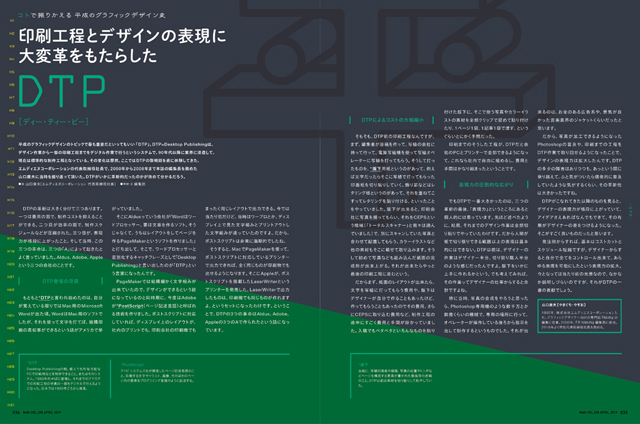
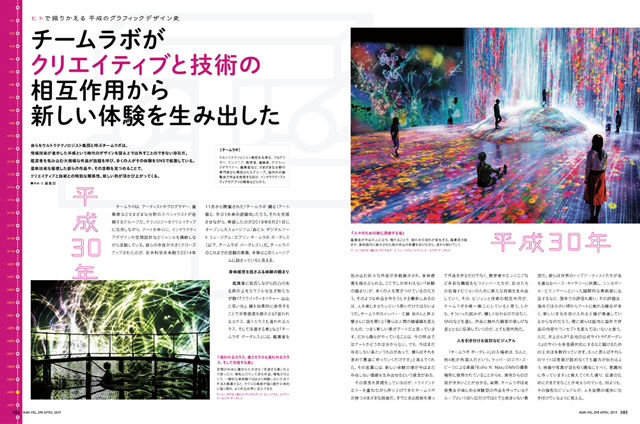
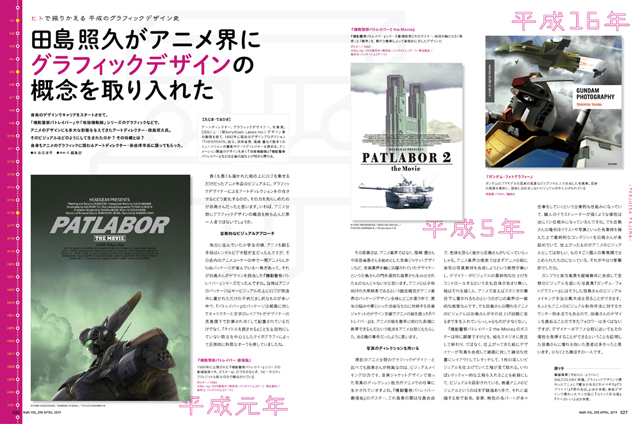
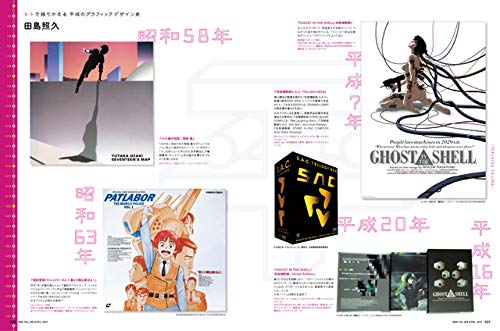
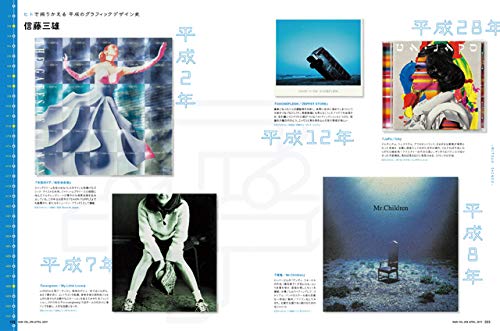
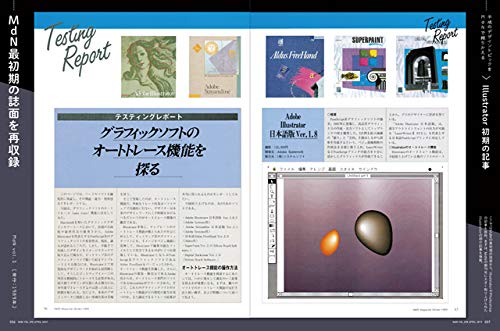
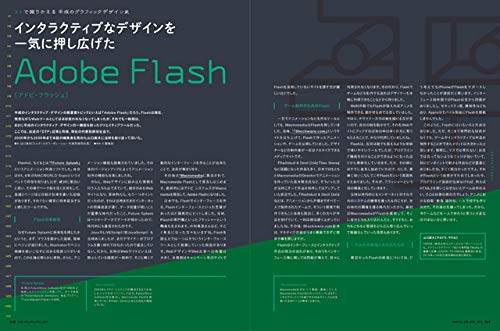
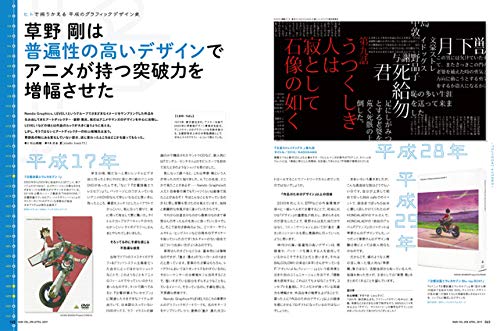
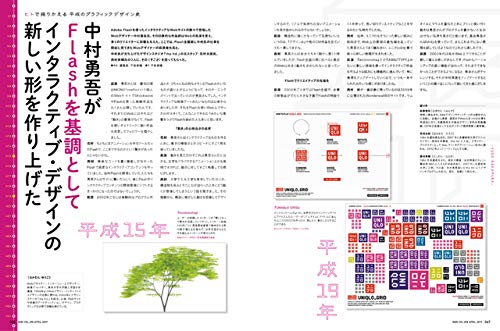
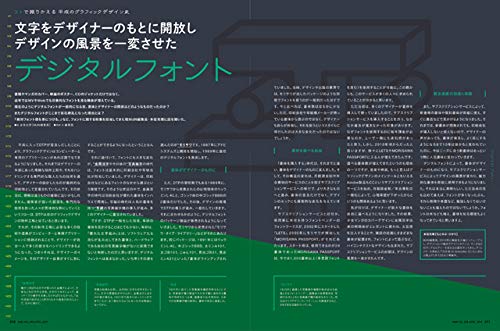
◆築地体後期五号
現代明朝体の始祖となるもぎたての果実のような成果
◆秀英明朝
改良を重ねて今がいちばん美味しい伝統の味わい
◆秀英初号明朝
江戸のクラシカルな香りが漂う粋な見出し明朝体
◆精興社書体
門外不出の格調高い一品。美しい謎に包まれた味
◆石井中明朝体(MM-OKL)
天才が手間ひまかけて美味をやさしく抽出した文字
◆イワタ明朝体オールド
文学を目でなめらかに十全に味わえる孤高の明朝体
◆モトヤ明朝
公的な場面で味わいたい、晴れがましさを感じる一品
◆凸版文久明朝
優しい軽みのある味わいでスッキリ爽やかテイスト
◆本明朝
刺激的で硬いテイスト。でもこの刺激、覚えがある?
◆A1明朝
情感あふれる味わい。言葉を選ぶほどの文字の個性
◆本蘭明朝
先進的な思想の明朝体。味わったことのないシャープさ
◆リュウミン
端正で落ち着いた表情。ひんやりとクールなテイスト
◆光朝
過去と未来が書体の中で交錯するハイブリッドな味覚
◆ヒラギノ明朝体
伝統をアップデートした雑味のない研ぎ澄まされた味
◆小塚明朝
機械的なまでに粒が揃った味わい。サイボーグ明朝体
◆丸明オールド
クラシカルでモダン。2つの異なる香りが広がる
◆游明朝体
この上質な味わいが新しい時代のスタンダードに
◆筑紫明朝
精製したばかりの米のように瑞々しく清潔な明朝体
◆筑紫Aオールド明朝
伝統の味わいを再定義、再構築したら新テイストに
◆第2期 筑紫明朝(筑紫アンティーク明朝/筑紫Q明朝/筑紫Aヴィンテージ明朝/筑紫Bヴィンテージ明朝)
伝統? 新創作? 明朝体の問題作といえる新テイスト
◆TP明朝
明朝体本来の情緒感を排したメカニカルなテイスト
◆貂明朝
かわいらしいけど媚びない飄々としたテイストの明朝
【登場する識者】※誌面登場順
祖父江 慎/小宮山博史/正木香子/橋本和夫/伊藤正樹/小野克之/藤田重信/鈴木 功/新井尚子/池田 暢/小塚昌彦/鳥海 修/草野 剛/西塚涼子/片岡 朗
■特別付録小冊子 明朝体テイスティングリスト
特集に連動した書体見本帳です。
特集で紹介する27種類の明朝体の書体見本と組み見本を掲載しています。
また書体の味わいを紹介する文章も用意しました。
LESSON 01 そもそも「フォント」ってなに?
LESSON 02 ひとつの書体だけど8つの書体?/03 フォントは誰かが時間をかけて作っている
LESSON 04 明朝体って単なる筆文字? 違います!
LESSON 05 明朝体にもいろんな「味」がある/06 アップデートされた新時代の明朝体
LESSON 07 ゴシック体は文字の骨組みがまるはだか!
LESSON 08 ゴシック体は2つの方向性に進化!/09 丸ゴシック体はゴシック体の妹分
LESSON 10 楷書体は明朝体のお兄さん?/11 伝統書体系はそのカタチに歴史あり
LESSON 12 デザイン書体は造形が本当に自由!/13 カッチリ系のデザイン書体も!
LESSON 14 文字の「明るさ」で書体を見抜く/15 文字の「部品」で書体の特徴をつかむ
〈実践編〉
書体の特徴はディテールに表れる
文字の「明るさ」はふところの広さ?
ひらがなの形が見分ける最大のヒント?
反ってる? まっすぐ? ゴシック体の梁(はり)に注目
「丸み」を観察して丸ゴシックを見分ける
文字の「余白」と「リズム」で雰囲気の違いを感じる
明朝体の長文を眺めて絶対フォント感を発動させよう!
ゴシック体の長文を見て絶対フォント感を働かせる!
〈深読み編〉
文字が加工されて、書体を見抜きにくい場合も!
一つの文章の中で漢字とかなの書体が違う?
普通の明朝体となにか違う? 新聞明朝のヒミツ
生まれながらに長体。コンデンス書体
どう使うかが試される? 極太・極細フォントブーム到来!
現代にチューンナップされる、新思想の明朝・ゴシック体
―フォントを読む! ―
書体史研究家・小宮山博史インタビュー
『文字の食卓』著者、正木香子の綴るエッセイ
―フォントを観る! ―
鉄道と文字が好きな人のためのWebマガジン〈もじ急行〉PRESENTS
「もじ鉄のススメ! 」&「えきもじ探訪 京浜急行電鉄編」